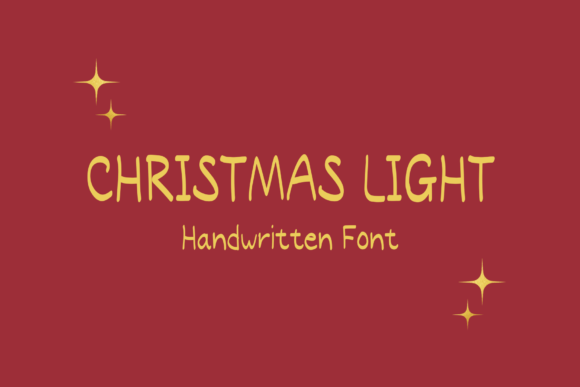
Christmas Light
Elaborado con precisión, Christmas Light proporciona vectores limpios, tipografía suave y una licencia comercial para tu tranquilidad.
Ya sea que estés creando productos POD (impresión bajo demanda), invitaciones de boda o gráficos para redes sociales, Christmas Light es una opción ideal.